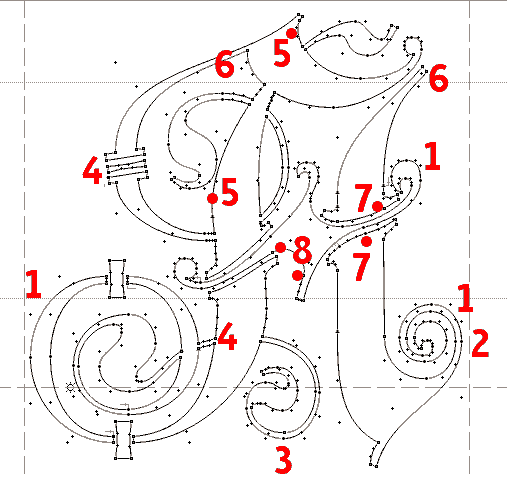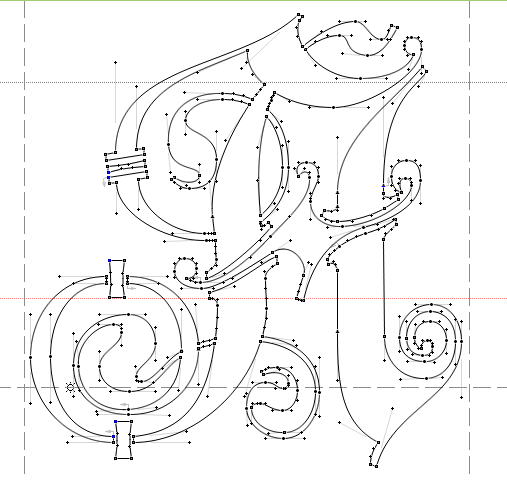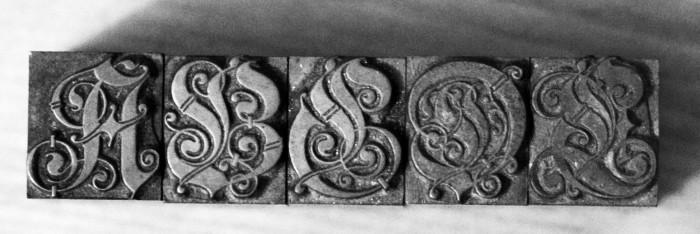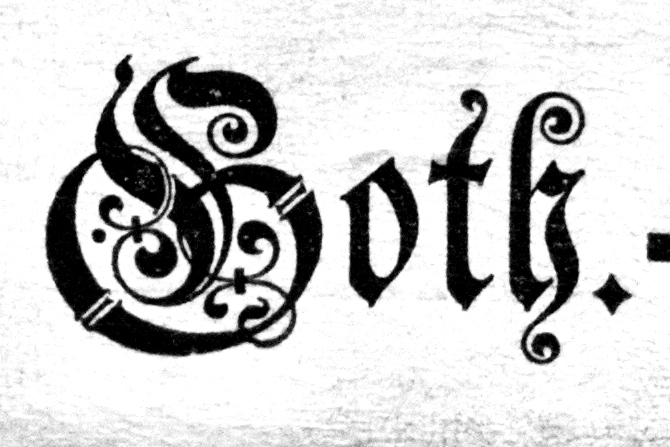
Unbekannte Bleisatzschrift (verzierte Gebrochene)
Hallo, ich habe einen Kasten mit einer verzierten, gebrochenen Bleisatzschrift, die ich nicht benennen kann. Die beiden angehängten Bilder sind die Beschriftung des Kastens und (bereits seitenrichtig) die Lettern ABCDE; bei Bedarf kann ich in ein paar Tagen auch eine Probe drucken und ein Bild davon hochladen. Kennt jemand diese Schrift? Vielen Dank, Thomas
Benennen kann ich die jetzt auch leider nicht, aber ich hätte einen großen Wunsch:
Wäre es möglich, so wie die Buchstaben A-E abgelichtet sind auch Fotos von allen weiteren Figuren zu machen. Davon würde ich gerne einen Font erstellen - und das nach Abbildungen der Letter selbst zu zeichnen, hätte einen großen Vorteil, da ich so auch die Original-Metriks der Schrift in den Font übernehmen kann.
Klar kann ich Fotos aller Figuren machen – d.h. all derer, die enthalten sind. M und ü fehlen nämlich leider. Das wäre dann die Anschlußfrage gewesen: Falls die Schrift bestimmbar ist, kann jemand die fehlenden Figuren beisteuern?
Das mit dem M ist zwar schade, ich werde das aber wohl mit den Kontruktionsprinzipien einer Gotischen und den Verzierungen der anderen Buchstaben wohl passend, wenn auch nicht unter Garantie identisch nachbauen können. Das ü ist dagegen gar kein Problem.
Wenn sich nicht doch ein Originalname auftreiben lässt, schlage ich dann als kleinen Dank für die bereitstellung der Vorlagen "Lotze-Gotisch" vor.
der erste M-Versuch:
@catfonts:
Achtung, bitte: die Kreissegmente sehen gegenüber dem Original leider nicht rund, sondern abgeflacht aus. Ich sehe insgesamt viele Ankerpunkte, die sehr ungünstig gesetzt sind und den Kurvenverlauf schlecht beeinflussen.
Ak ja, wo siehst du die Ankerpunkte? Die setze ich nämlich sehr wohl mit bedacht, und wenn ein Bogen noch ein wenig Nachrundung braucht, geht das im Font-Editor dann noch schöner, da ich hier, da Ankerpunkte aufs Raster rücken, ohnehin nich Feinjustagen nötig sind.
Auf alle Fälle setze ich die Ankerpunkte nach Möglichkeit auf die Extreme, sodass sie mit den Kontrollvektoren auf einer waagerechten oder senkrechten Linie sitzen, das mildert Rundungsfehler:
Und jetzt verrate ich mal noch ein bisschen meine Methode:
1. Ich zeichne zuerst gerade Freihandlinien von Extrempunkt zu Extrempunkt der Kurve, hierdurch sehe ich am besten, dass meine Knoten wirklich an den Extremen sitzen.
2. Dann wandele ich die Geraden in Kurven, und ziehe sie grob in die gewünschte Rundung. dabei schieße ich einen Hauch übers Ziel hinaus, da die Knoten noch spitz sind.
3. Abschließend werden die spitzen Knoten in glatte Knoten geändert (sofern nicht eine Spitze vorliegt, natürlich, und die Kontrollvektoren waagerecht und Senkrecht ausgerichtet, der kleine Eingriffe in die Länge der Kontrollvektoren wird dann der Kurvenabschnitt auf die Kontur des Pixelbildes gelegt. Viele Korrekturen sind da oft nicht nötig.
Und dann geht's mit der nächsten Kontur von Vorn los...
@catfonts:
Ich muss vorausschicken, dass ich deine Arbeit keinesfalls bemängeln wollte. Aus verschiedenen Gründen muss ich in einer Zeichnung sofort beurteilen können, ob die Ankerpunkte optimal gesetzt sind. Daher meine Bemerkung weiter oben. Sie bezog sich auf die überzeichnete Letter zu Beginn des Threads. Abgeflacht meinte, dass die Bögen an den Ankerpunkten zu flach werden. Anders gesagt: Der Kurvenbogen ist überzogen, weil die Anfasser zu weit herausstehen. Nimm die Drittel-Regel: Ein Anfasser ragt nur zu einem Drittel in den Kurvenbogen.
Anhand deiner Beziér-Abbildung fallen mir außerdem noch weitere Dinge auf:
1= Überzogene Kurven
2= Senkrechte ist dünner als Waagerechte
3= Kurvenpunkt steht falsch
4= Anfasser sind verzogen
5= Ankerpunkt fehlt
6= Anfasser geht in die falsche Richtung
7= Kurvenpunkt überflüssig
8= Kurvenpunkte nicht an den Extremen
Wie gesagt: Es ist mir halt aufgefallen. Der äußerste Punkt einer Kurve ist nicht immer eindeutig festzustellen.
@ tlotze:
Allein, dass du eine Schriftart zum Leben erwecken willst, ist von großer Bedeutung.
Lass den Arbeitstitel doch einfach zu. (Wobei ich jedoch weiß, was du meinst.)
@catfonts:
Deine Entwürfe sehen sehr vielversprechend aus. Ich bin gespannt, wie du weiter vorankommst. Eine Fraktur ist heutzutage eher untypisch, ich arbeite selber an einem Entwurf.
Bitte, lass uns daran teilhaben: Ich hege großen Respekt vor deiner Arbeit und möchte gern behilflich sein.